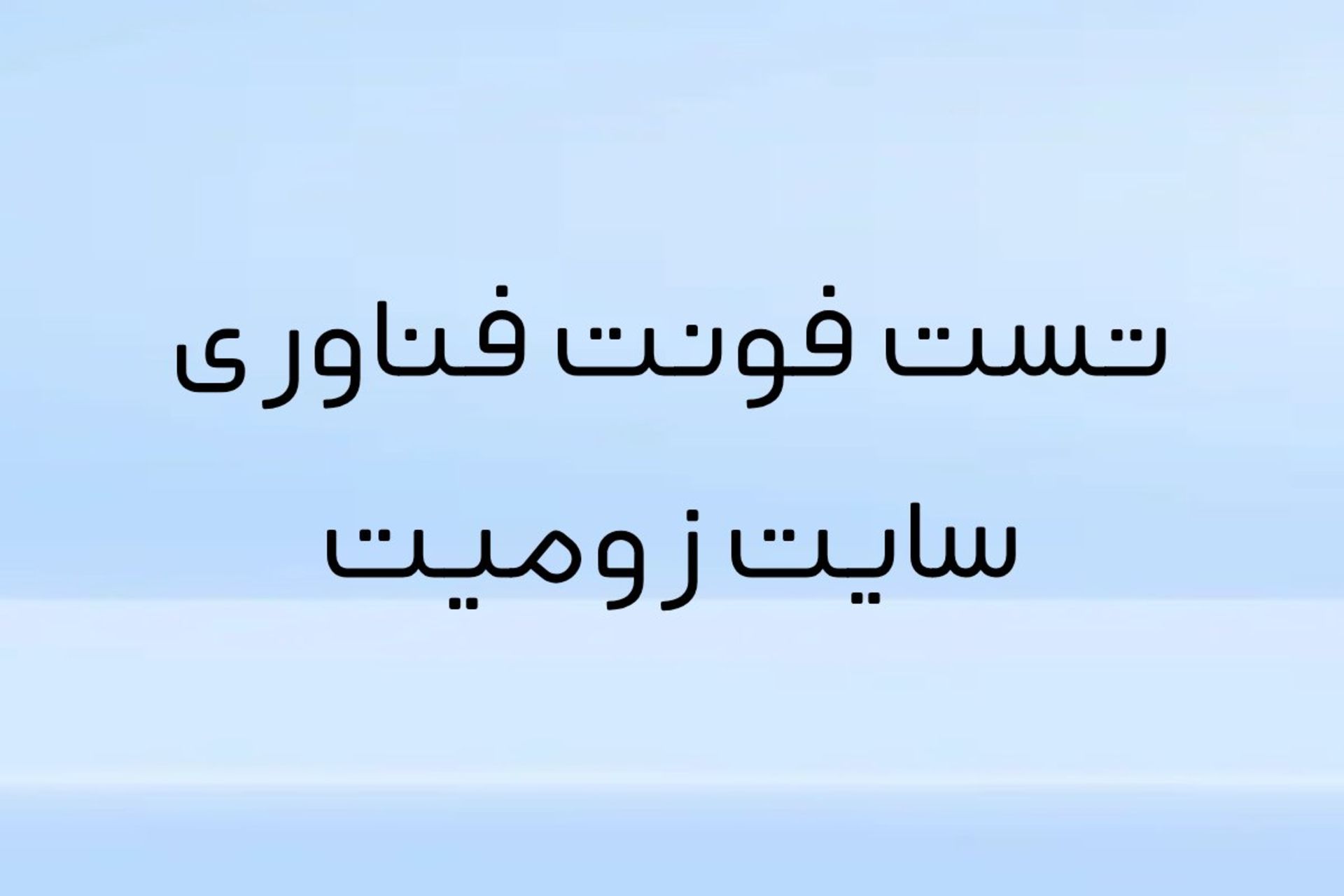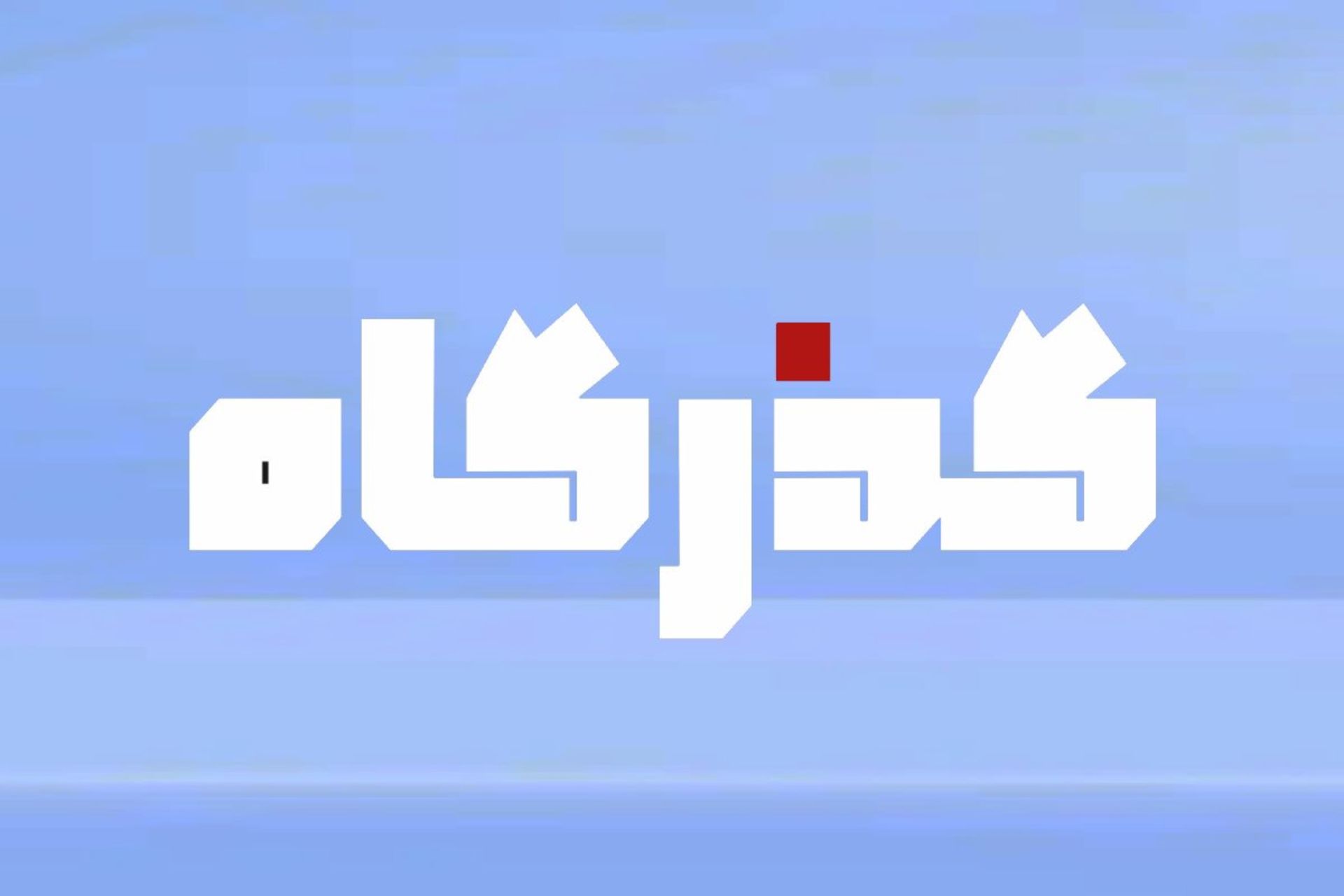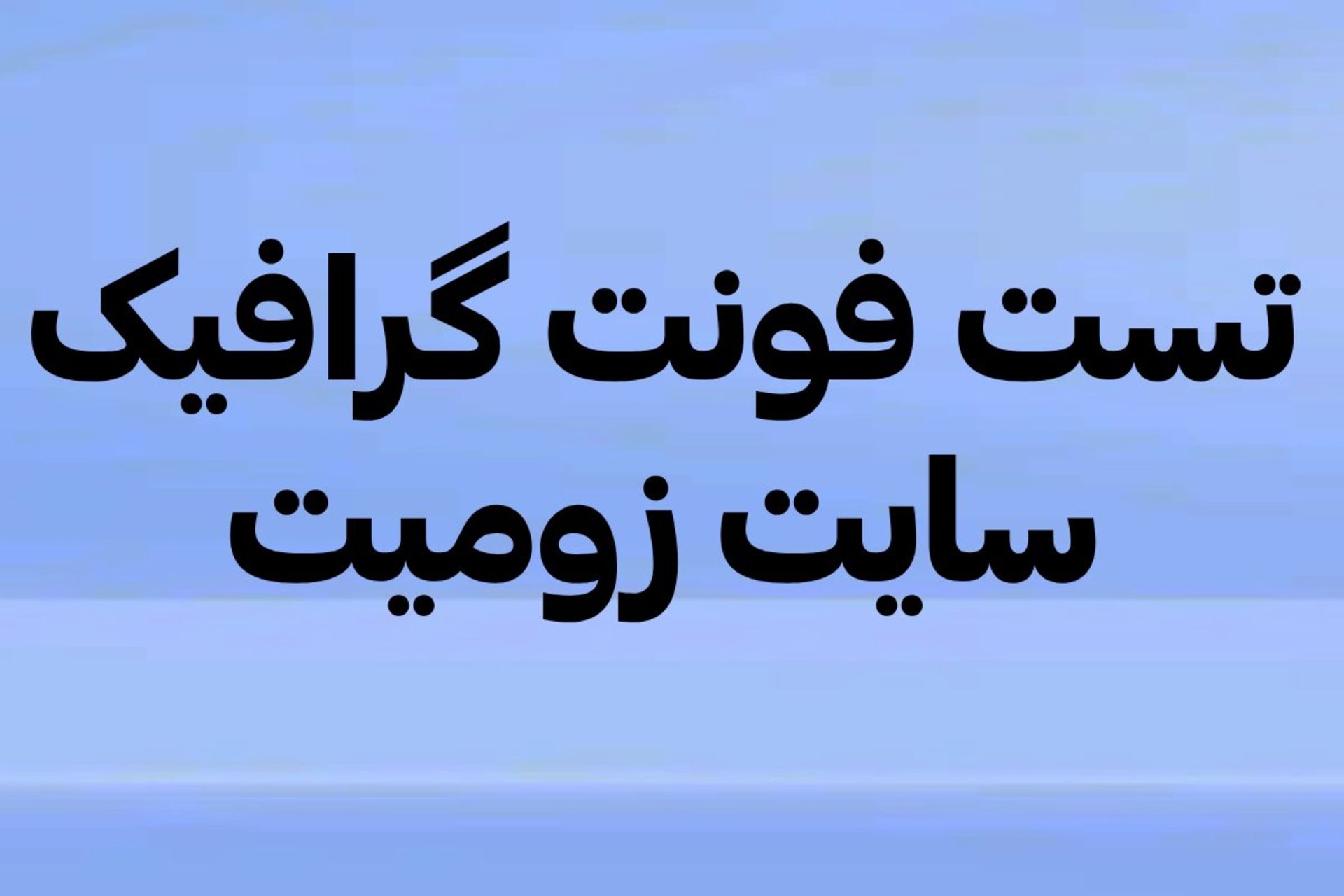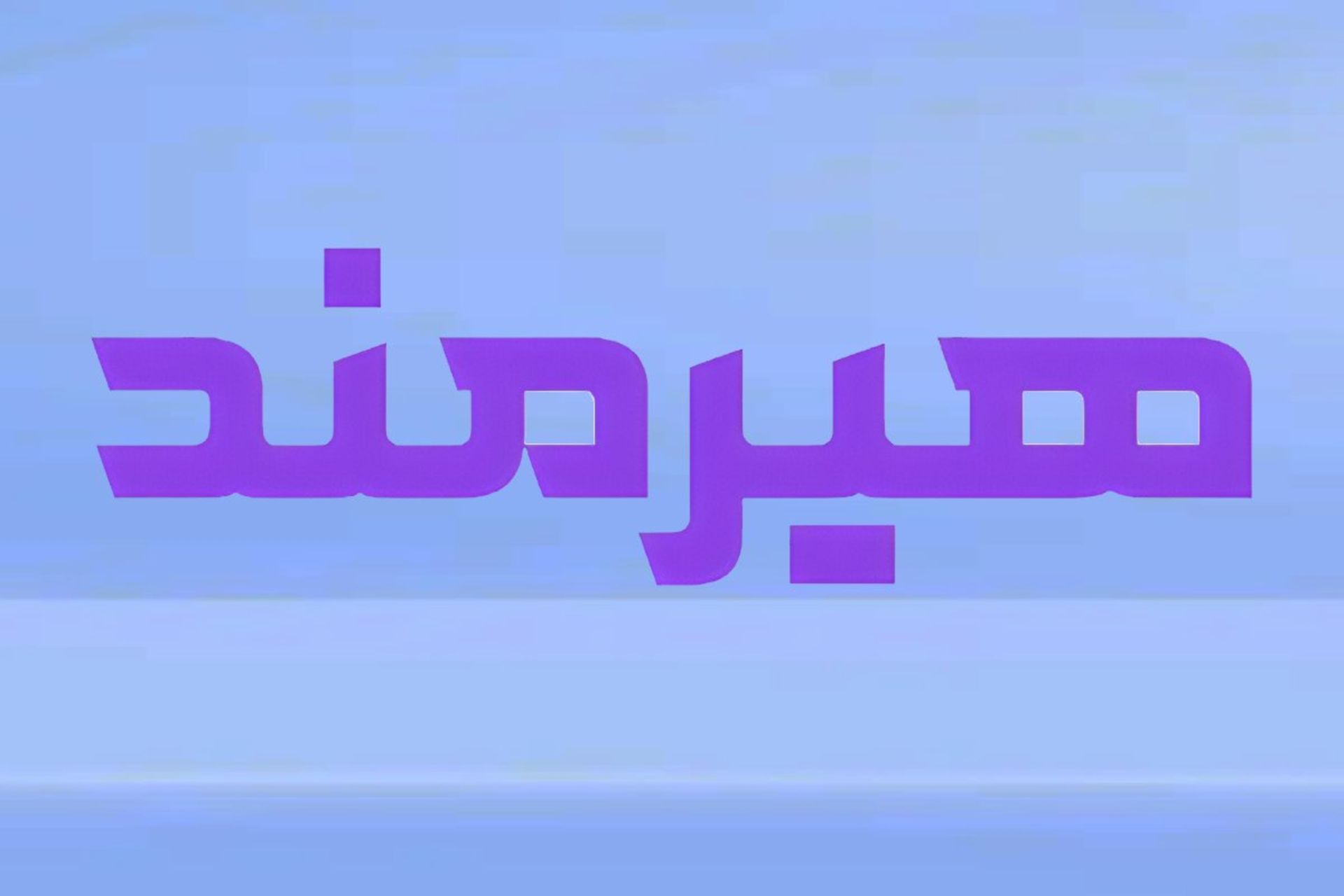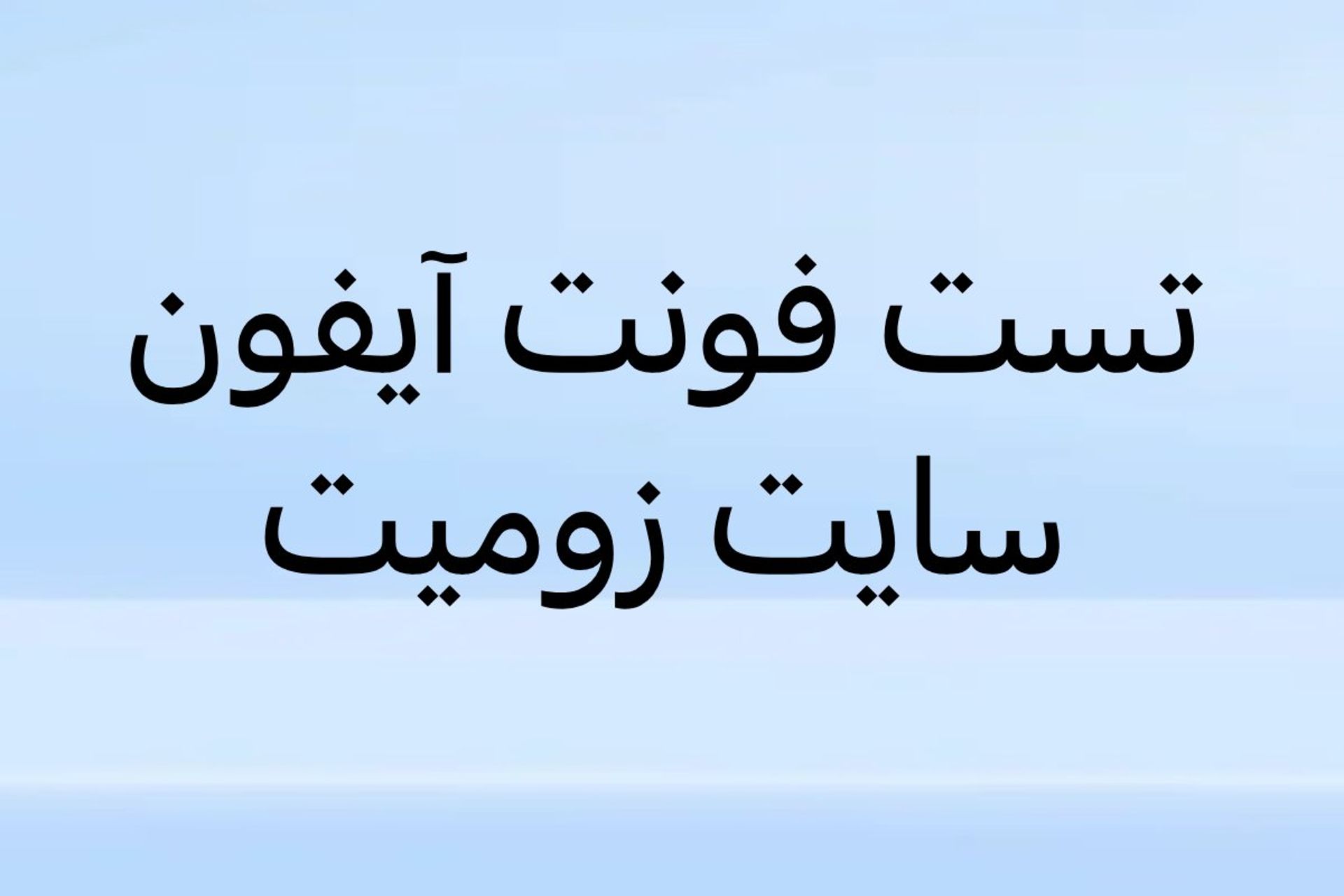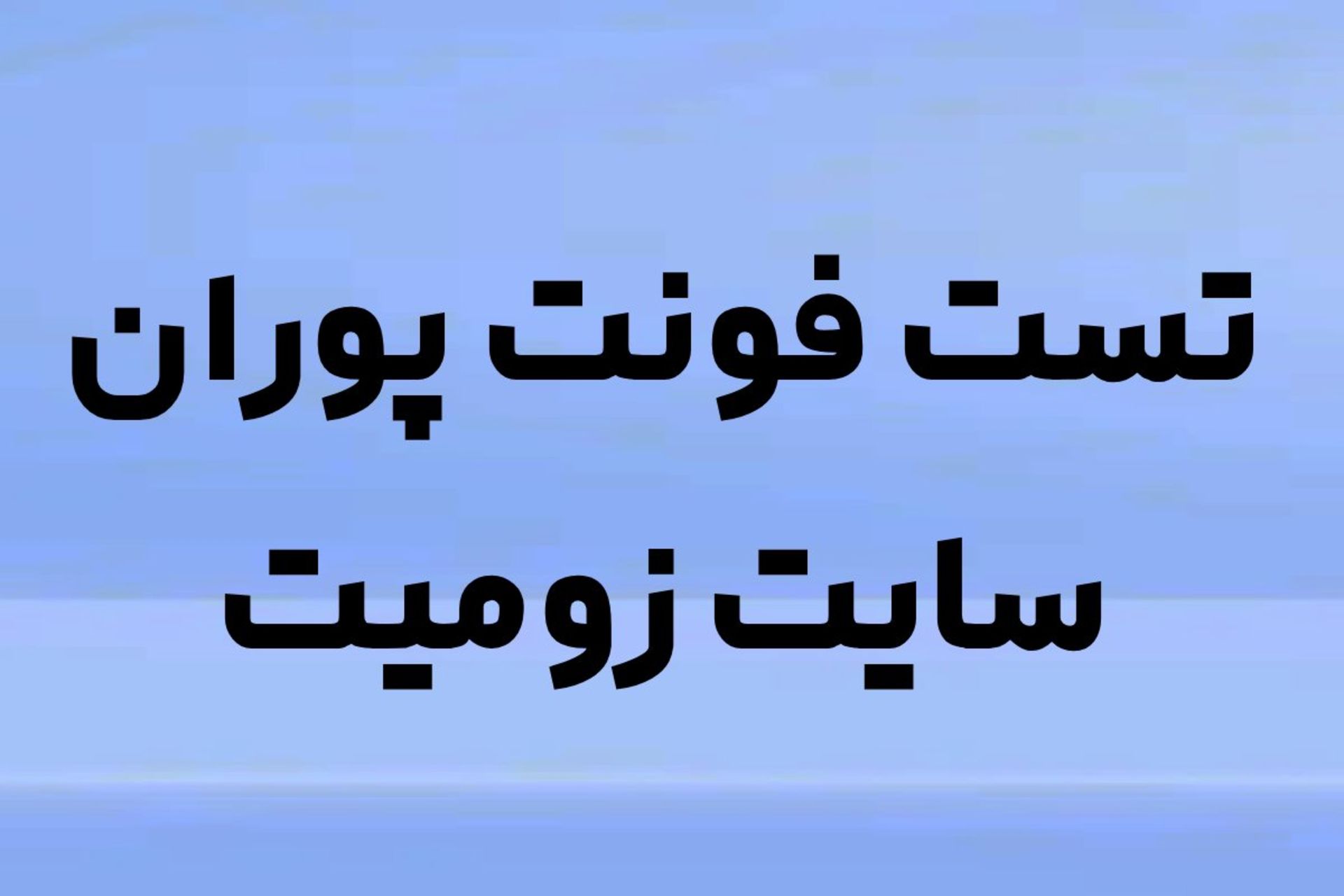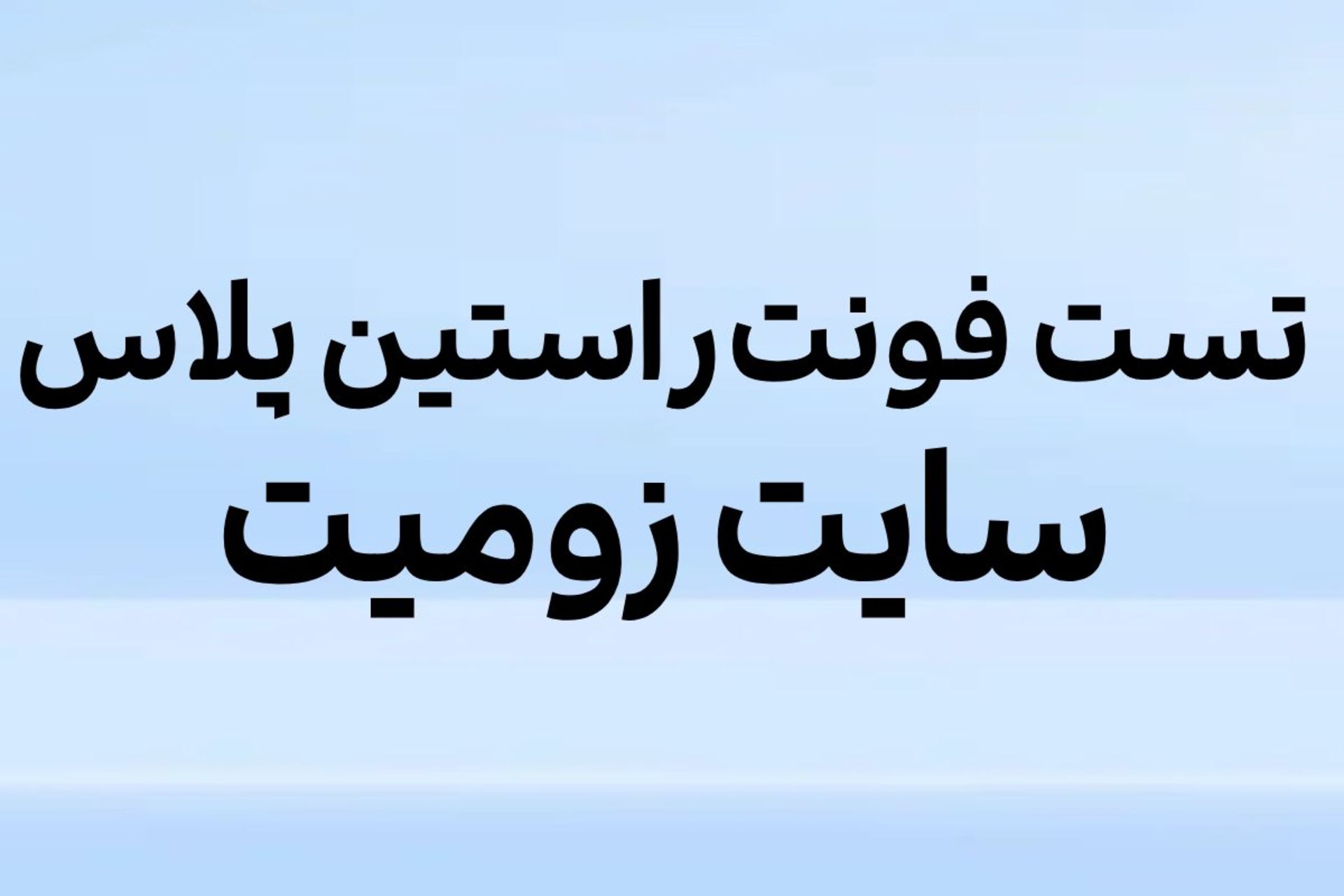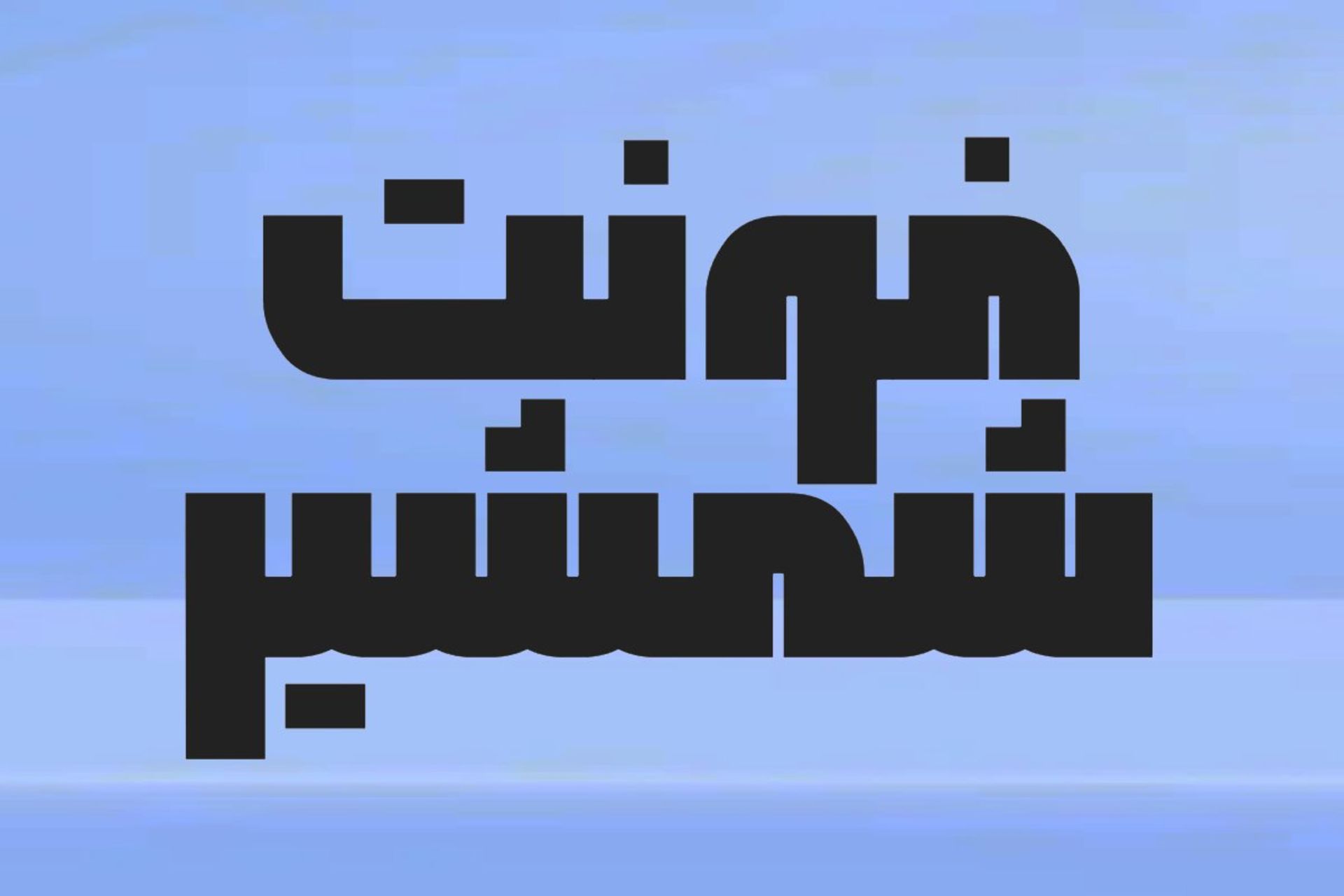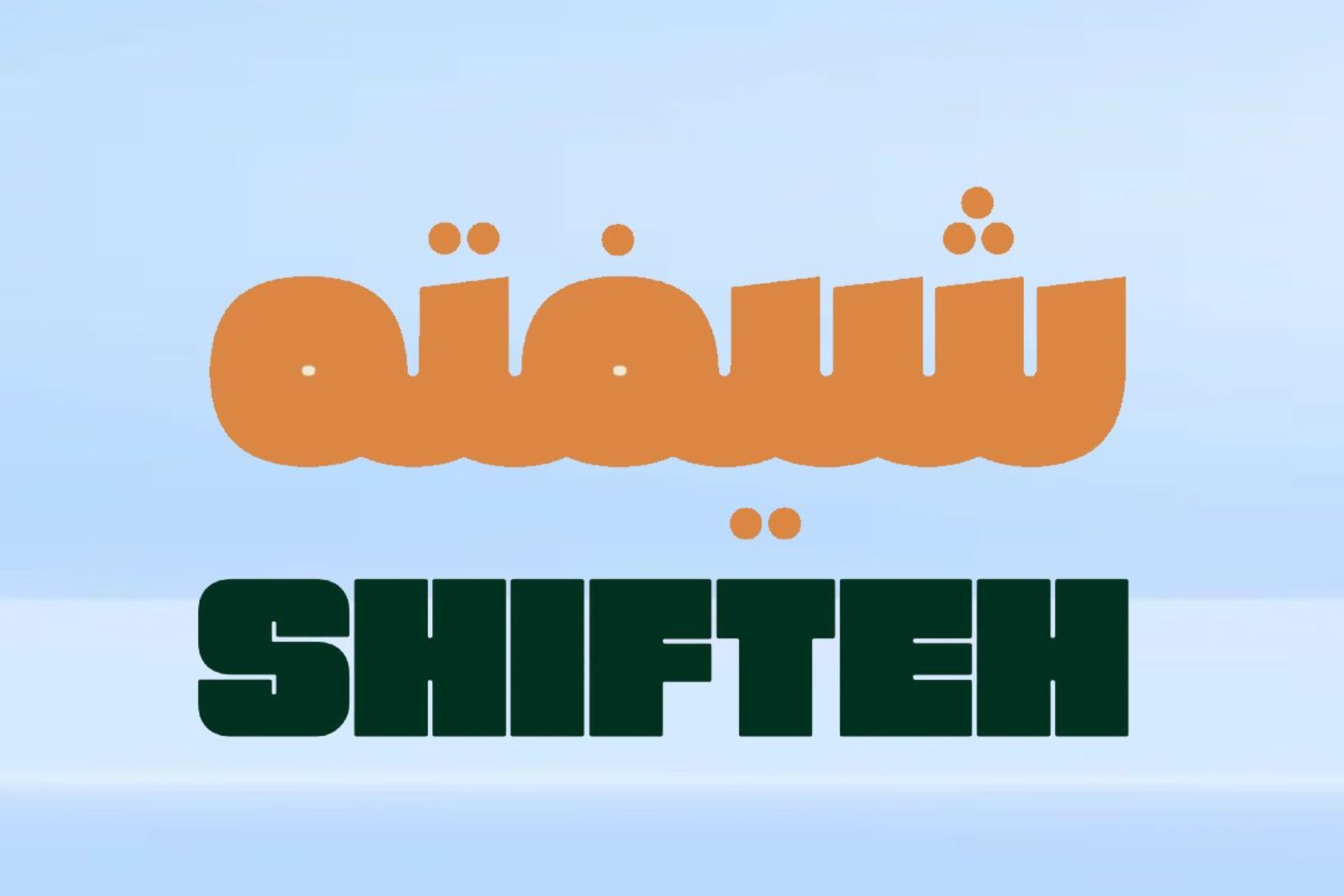
بهترین فونت ها برای کاور ویدیو در اینستاگرام و یوتیوب
فونت برای طراحی تامبنیل یوتیوب و اینستاگرام
کاور ویدیو فقط یک تصویر نیست؛ انتخاب درست فونت می‌تواند راز تفاوت بین کلیک ساده و نادیده‌گرفتن کامل محتوای شما باشد.
در شبکه‌های اجتماعی که کاربران با سرعت بالا محتوا را مرور می‌کنند، چند ثانیه‌ی اول سرنوشت‌ساز است. حتی حرفه‌ای‌ترین ویدیو هم بدون یک کاور جذاب به‌راحتی نادیده گرفته می‌شود. ساخت کاور برای کانال یوتیوب یا اینستاگرام حکم ویترین محتوا را دارد؛ ویترینی که می‌تواند کاربر را برای کلیک وسوسه کند. در این میان، فونت نقش مهمی در طراحی دارد؛ انتخاب درست آن علاوه‌بر زیبایی، پیام را سریع‌تر منتقل کرده و هویت برند را تقویت می‌کند.
در تامبنیل‌های فارسی اما انتخاب فونت چالش‌برانگیزتر است، چون بسیاری از فونت‌های رایج برای ابعاد کوچک یا نمایش سریع مناسب نیستند. بنابراین باید سراغ فونت‌هایی رفت که هم خوانایی بالا داشته باشند و هم با فضای بصری یوتیوب و اینستاگرام هماهنگ باشند.
فونت فناوری
فونت «فناوری» یکی از مدرن‌ترین فونت‌های فارسی است که با طراحی ساده و امروزی، میان تولیدکنندگان محتوا محبوب شده است. این فونت در دو سایز عرضه می‌شود و ترکیبی از سادگی مینیمال و جدیت حرفه‌ای را ارائه می‌دهد.
ویژگی برجسته‌ی آن، وضوح بالا در ابعاد کوچک است؛ بنابراین حتی روی تامبنیل‌های یوتیوب و اینستاگرام هم خوانایی خود را حفظ می‌کند. همین خصوصیت، فونت «فناوری» را گزینه‌ای مناسب برای محتوای آموزشی، فناوری یا نقد و بررسی محصولات می‌سازد.
فونت آیفون
شاید نام این فونت شما را یاد برند اپل بیندازد، اما فارغ از این شباهت، فونت «آیفون» با داشتن ۹ وزن متنوع، یکی از انعطاف‌پذیرترین گزینه‌ها برای طراحی تامبنیل به‌شمار می‌رود.
فونت آیفون به‌دلیل سبک ساده و پرقدرتش، تقریباً با هر نوع محتوایی سازگار است. اگر کانالی دارید که طیف وسیعی از ویدیوها را منتشر می‌کند، از نقد فیلم گرفته تا آموزش نرم‌افزار، فونت آیفون می‌تواند انتخابی مطمئن باشد.
فونت گرافیک
فونت «گرافیک» از سال‌ها قبل به‌عنوان یکی از پرکاربردترین فونت‌های تبلیغاتی شناخته می‌شود و احتمالاً آن را در بسیاری از تامبنیل‌های یوتیوب دیده‌اید. علت محبوبیت آن، ترکیب ظاهری خاص و چندمنظوره بودن است. این فونت حالتی شیک و چشم‌نواز دارد و برای طراحی تامبنیل‌هایی که باید کمی متفاوت و خاص به‌نظر برسند، انتخاب فوق‌العاده‌ای محسوب می‌شود.
اگر محتوای شما در زمینه‌های هنری، موسیقی یا طراحی فعالیت دارد، فونت گرافیک می‌تواند هویت بصری کانال‌تان را برجسته‌تر کند. این فونت به‌دلیل شناخته‌شده بودنش، نوعی اعتبار و حس حرفه‌ای بودن نیز به همراه دارد.
فونت تیتر پلاس
فونت «تیتر پلاس» نسخه‌ی به‌روزشده‌ی فونت محبوب «تیتر» است که سال‌ها در طراحی‌های مختلف مورد استفاده قرار می‌گیرد. این نسخه‌ی جدید با سه وزن متفاوت منتشر شده است و انعطاف‌پذیری بالاتری نسبت به نسخه کلاسیک دارد.
تیتر پلاس برای کاورهایی که باید رسمی، جدی و حرفه‌ای باشند، انتخاب ایدئالی است. بسیاری از کانال‌های خبری یا تحلیلی از این فونت استفاده می‌کنند زیرا اعتبار و رسمیت را به تصویر می‌کشد. علاوه‌بر این، می‌توانید با وزن‌های متنوعش هم تیتر اصلی و هم زیرعنوان‌های تامبنیل را با هماهنگی طراحی کنید.
فونت راستین پلاس
نسخه‌ی ارتقاءیافته‌ی فونت راستین یعنی «راستین پلاس»، برای کسانی طراحی شده است که دنبال ظاهر حرفه‌ای و کیفیت بالا هستند. این فونت علاوه‌بر پشتیبانی کامل‌تر از زبان فارسی، نسخه‌ی انگلیسی نیز دارد که امکان استفاده‌ی دو زبانه را در یک تامبنیل یوتیوب یا اینستاگرام یا هر طرح گرافیکی دیگری فراهم می‌کند.
ویژگی بارز فون راسین پلاس، قدرت در انتقال حس رسمی و جدی است. به همین دلیل برای تامبنیل‌هایی که قرار است محتوای تحلیلی، سیاسی یا خبری را معرفی کنند، گزینه‌ای ایدئال محسوب می‌شود. نسخه‌ی جدید آن با وزن‌های بیشتر، دست طراح را برای انتخاب باز گذاشته است
فونت شیفته
فونت «شیفته» برخلاف نام آرام و شاعرانه‌اش، ظاهری قدرتمند و هندسی دارد. ساختار ساده اما پرقدرت و ضخیم این فونت باعث شده است برای تیترهای کوتاه و پرانرژی بسیار مناسب باشد.
فونت شیفته در دو وزن طراحی و نسخه‌ی انگلیسی آن نیز ارائه شده است. همین ترکیب، امکان هماهنگی بین زبان‌ها را فراهم می‌کند. اگر محتوای کانال شما مرتبط با سرگرمی، ورزش یا موضوعات پویاتر است، فونت شیفته می‌تواند انرژی لازم را به تامبنیل منتقل کند.
فونت گذرگاه
یکی از جدیدترین فونت‌های فارسی در حوزه طراحی گرافیکی، فونت «گذرگاه» است. این فونت به خاطر ضخامت زیاد و استایل برجسته‌اش، برای تامبنیل‌هایی که قرار است پیام در یک نگاه منتقل شود، فوق‌العاده عمل می‌کند.
اگر به دنبال جذب مخاطب در فضایی مانند یوتیوب یا اینستاگرام هستید که پر از رقابت است، گذرگاه می‌تواند انتخاب طلایی شما باشد. این فونت برای محتوای آموزشی سریع، کلیپ‌های انگیزشی یا حتی ویدیوهای طنز که نیازمند جلب توجه فوری هستند، بسیار کاربردی است.
فونت هیرمند
فونت «هیرمند» جزو فونت‌هایی است که با قدرت بصری بالا و ضخامت خاصش می‌تواند به‌راحتی نگاه مخاطب را در چند ثانیه جذب کند. این فونت به‌ویژه برای کاورهایی که باید در بین انبوهی از تامبنیل‌ها متمایز باشند، بسیار مؤثر است.
یکی از ویژگی‌های جالب هیرمند، جسارت در طراحی است. ضخامت و استایل بولد آن باعث می‌شود متن مانند برچسبی پررنگ روی تصویر قرار گیرد. اگر محتوای کانال شما در حوزه‌های ورزشی، هیجانی یا حتی نقد اجتماعی است، این فونت زیبا می‌تواند حس قدرت و جدیت را به‌خوبی منتقل کند.
فونت پوران
فونت «پوران» فضایی دوستانه، گرم و کمی غیررسمی دارد. این فونت به‌گونه‌ای طراحی شده که احساس نزدیکی و صمیمیت را القا کند؛ بنابراین برای ویدیوهایی مثل ولاگ‌های روزانه، محتوای سبک زندگی یا آموزش‌های عمومی، بسیار مناسب است.
نکته‌ی مثبت پوران این است که برخلاف برخی فونت‌های هنری که ممکن است خوانایی پایینی داشته باشند، در ابعاد کوچک هم وضوح خوبی ارائه می‌دهد. این یعنی حتی اگر مخاطب روی موبایل و با سرعت در حال مرور باشد، پیام شما گم نخواهد شد.
فونت شمشیر
فونت «شمشیر» ترکیبی از سادگی هندسی و قدرت بصری است. ظاهر آن در عین آرامش، نوعی استواری و قاطعیت را منتقل می‌کند. درحال حاضر فقط یک وزن از این فونت منتشر شده است، اما طبق گفته‌ی طراحان، در آینده وزن‌های بیشتری ارائه خواهد شد.
فونت شمشیر برای ویدیوهایی که محتوای انگیزشی، جدی یا حتی آموزشی سنگین دارند، مناسب است. حس جنگجویی و قدرتی که از اسم و ظاهر این فونت به ذهن می‌رسد، می‌تواند انرژی تامبنیل شما را چند برابر کند.
چگونه بهترین فونت را برای کاور انتخاب کنیم؟
حالا که با فونت‌های پرکاربرد و جذاب برای ساخت تامبنیل آشنا شدیم، شاید این سؤال پیش بیاید که از بین آن‌ها کدام یک مناسب‌ترین گزینه برای شما است. انتخاب فونت بستگی به چند عامل کلیدی دارد:
• نوع محتوا: اگر ویدیوهای آموزشی و رسمی تولید می‌کنید، فونت‌هایی مثل فناوری، راستین پلاس یا تیتر پلاس بهترین انتخاب هستند. برای ولاگ‌ها یا محتوای سبک زندگی، فونت پوران حس صمیمیت بیشتری منتقل می‌کند.
• هویت برند: کانال‌هایی که به دنبال ظاهر مدرن و مینیمال هستند، می‌توانند از فونت‌هایی مانند آیفون یا فناوری بهره ببرند.
• رقابت بصری: در محیط شلوغی مثل یوتیوب، فونت‌هایی پرقدرت و ضخیم مثل هیرمند و گذرگاه به شما کمک می‌کنند بیشتر دیده شوید.
• انعطاف‌پذیری: فونت‌هایی مانند آیفون یا راستین پلاس با وزن‌های متنوع، آزادی عمل بیشتری برای طراحی فراهم می‌کنند.
• آیا انتخاب فونت روی بازدید ویدیو تأثیر دارد؟
بله، فونت مناسب می‌تواند در چند ثانیه اول توجه کاربر را جلب کند و احتمال کلیک روی ویدیو را افزایش دهد.
• بهترین فونت برای تامبنیل ویدیوهای آموزشی کدام است؟
فونت‌هایی مثل «فناوری»، «تیتر پلاس» و «راستین پلاس» به دلیل خوانایی بالا و ظاهر رسمی برای محتوای آموزشی بهترین گزینه‌اند.
• آیا باید در همه تامبنیل‌ها از یک فونت ثابت استفاده کنیم؟
بهتر است یک یا دو فونت اصلی را به‌صورت ثابت به کار ببرید تا هویت بصری کانال حفظ شود، اما می‌توانید برای ویدیوهای خاص از فونت متفاوت هم استفاده کنید.